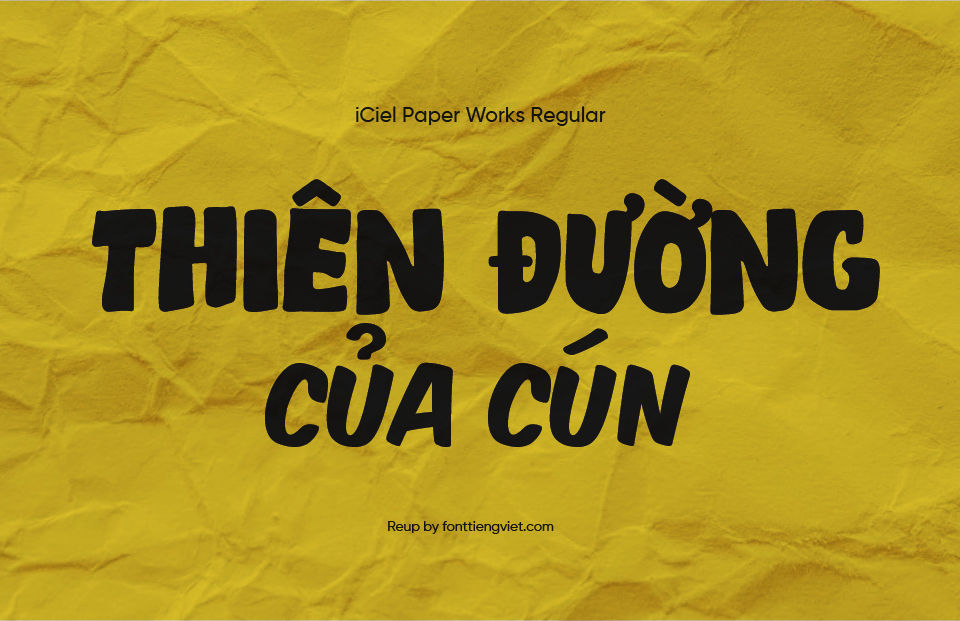
Font Việt hóa iCiel Paper Works là một trong những bộ phông chữ độc đáo nhất dành cho những ai yêu thích phong cách thủ công, cắt dán. Được lấy cảm hứng từ những mẩu giấy cắt tay tỉ mỉ, bộ Font Chữ này mang lại cảm giác mộc mạc, gần gũi nhưng không kém phần nghệ thuật. Tại Việt Nam, cộng đồng thiết kế luôn săn đón iCiel Paper Works bởi tính ứng dụng cao trong các dự án học đường, trang trí báo tường hay làm thiệp chúc mừng. Việc sở hữu bản Việt hóa giúp người dùng dễ dàng truyền tải thông điệp bằng tiếng Việt một cách trọn vẹn mà không lo lỗi hiển thị ký tự đặc biệt.
Đặc điểm nổi bật của Font Việt hóa iCiel Paper Works
Thiết kế thủ công đầy ấn tượng
Điểm mạnh nhất của Font Việt hóa iCiel Paper Works chính là những đường nét không hoàn hảo một cách cố ý. Mỗi chữ cái giống như được cắt ra từ giấy màu, tạo nên hiệu ứng thị giác 3D thú vị. Điều này giúp các tiêu đề trở nên nổi bật và thu hút sự chú ý của học sinh cũng như giáo viên trong các bài giảng điện tử sinh động.
Khả năng ứng dụng đa dạng
Bộ font này cực kỳ phù hợp cho các thiết kế poster sự kiện, bìa sách thiếu nhi hoặc các video clip sáng tạo. Sự linh hoạt trong đường nét giúp iCiel Paper Works dễ dàng kết hợp với nhiều màu sắc rực rỡ, tạo nên một không gian thiết kế đầy năng lượng và vui tươi.
Để tối ưu hóa vẻ đẹp của Font Việt hóa iCiel Paper Works, bạn nên sử dụng cho các cụm từ ngắn hoặc tiêu đề chính thay vì văn bản dài. Hãy thử kết hợp thêm các hiệu ứng đổ bóng hoặc lồng ghép hình ảnh để tăng thêm độ chân thực cho chất liệu giấy. Hy vọng bộ font này sẽ trở thành trợ thủ đắc lực cho các bạn học sinh và nhà thiết kế. Chúc bạn có những tác phẩm tuyệt vời cùng Font Miễn Phí, Font Việt Hóa, Font Việt hóa iCiel Paper Works ngay hôm nay.